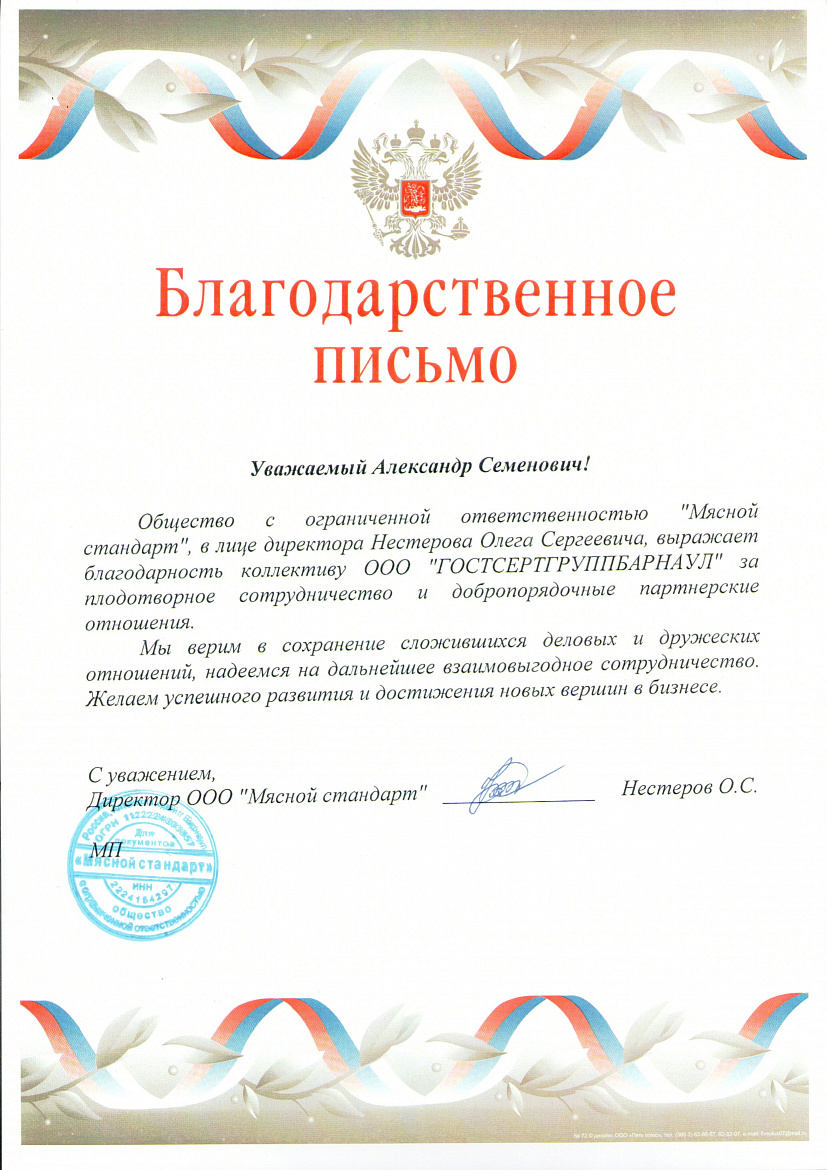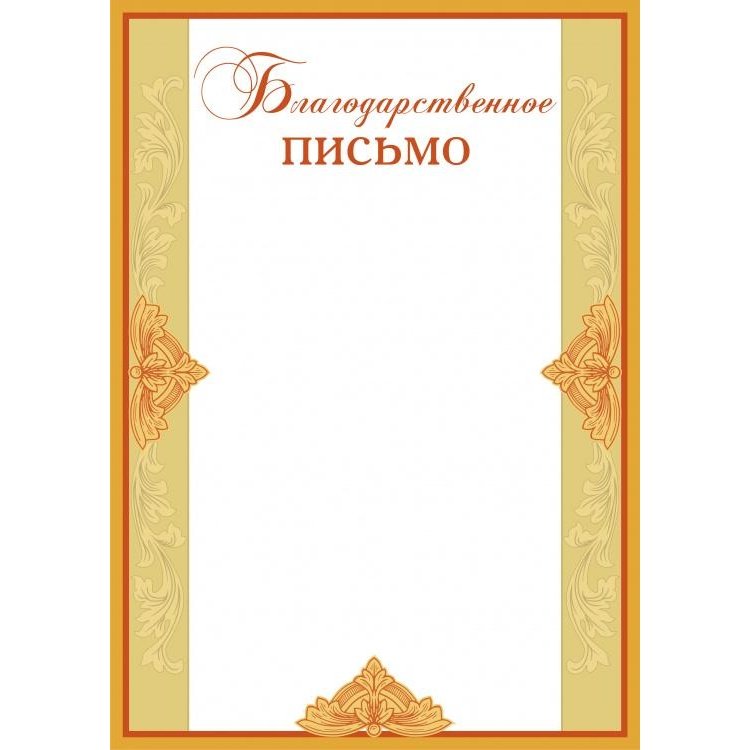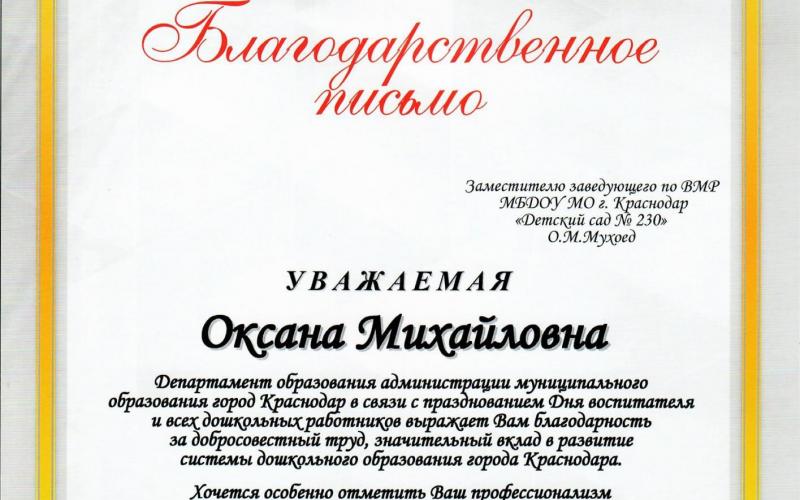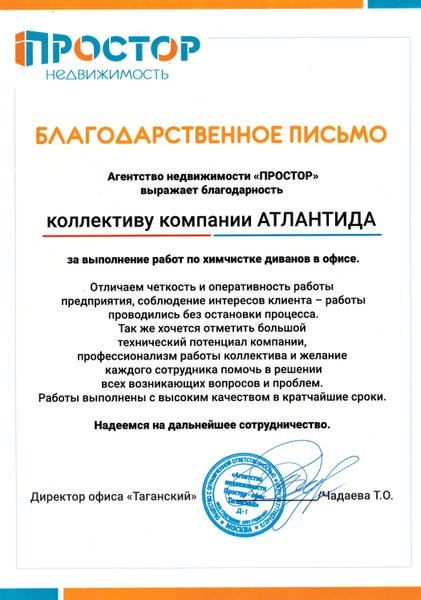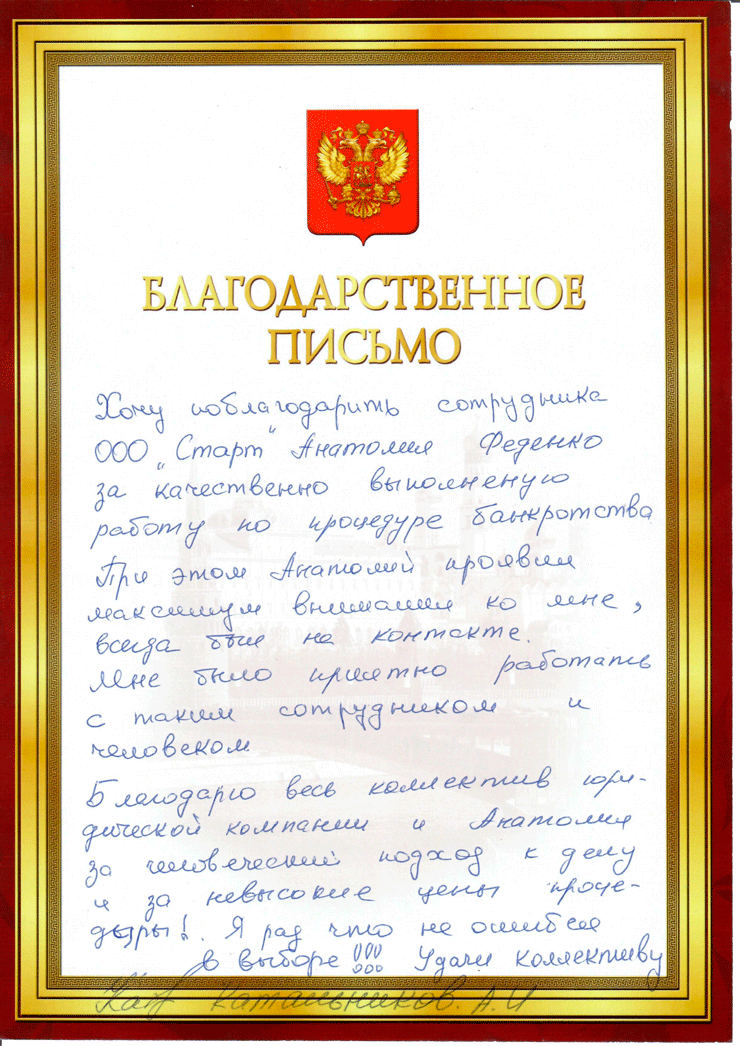
3 совета по правильному использованию шрифтов в электронных письмах / Хабр
Вы когда-нибудь задумывались о том, почему выбранный вами шрифт для электронного письма не отображался в почтовом ящике? Вероятно, это случалось, потому что ваш шрифт не был «безопасным», и устройство, на котором открывали письмо, его не поддерживало. В этой статье мы рассмотрим понятие «веб-безопасности» шрифтов, способы использования стандартных и нестандартных шрифтов, а также лучшие примеры их использования в email-рассылках.
Безусловно, одним из наиболее важных элементов проектирования является печатный текст. А графическое оформление и стиль текста называют типографикой. При правильном подходе типографика может преобразить ваши электронные письма. Однако проблема заключается в том, что не все шрифты отображаются во всех почтовых ящиках и на всех устройствах. Для начала нужно определиться с границами «веб-безопасности».
«Небезопасные» шрифты и как ими пользоваться
Определенные шрифты будут корректно отображаться абсолютно на всех устройствах и во всех почтовых клиентах.
Это так называемые «веб-безопасные» шрифты:
- Arial
- Courier
- Georgia
- Helvetica
- Lucida Sans
- Tahoma
- Times New Roman
- Trebuchet MS
- Verdana
А поскольку они отображаются везде, то вы можете смело использовать их в своих email-маркетинговых кампаниях. Единственным недостатком этих шрифтов является их весьма ограниченное количество.
В таком случае, что остается делать проектировщикам интерфейсов? К счастью, существует несколько способов решения этой проблемы.
Во-первых, при грамотной верстке писем нужно использовать не только шрифты, но и изображения, отступы, пробелы, работать с текстом и т. п. Об этом мы поговорим позже.
Во-вторых, выйти за границы «веб-безопасности» можно, набирая текст нестандартными шрифтами. Одним из популярных способов является использование веб-шрифтов, которые скачиваются при открытии сообщения, например, с сервиса Google web fonts.
А теперь давайте вернемся к проектированию электронных писем и типографике. Правильно подобрать шрифт для кампании email-маркетинга вам помогут 3 совета.
Совет №1: Выберите правильный шрифт для основного текста письма
В прошлом году на сайте компании Bloomberg была опубликована статья под названием «Шрифт ваших писем портит вам жизнь», автор которой пришел к выводу, что такие шрифты, как Arial и Helvetica не слишком подходят для чтения писем на ходу [мы уже переводили этот материал в нашем блоге – его можно прочитать
– прим. перев.]. Почему? Потому что формы некоторых букв – таких, как p, b, q, d – слишком схожи между собой, и читателю трудно их различить. «Вам следует использовать шрифт, в котором буквы не сливаются друг с другом», – дал совет профессор шрифтового дизайна Джерри Леонидас (Gerry Leonidas). Засечки, характерные для шрифтов семейства serif, придают каждой букве уникальность.
Напоминаем, как выглядят буквы с засечками и без них:
Какие шрифты рекомендуется использовать при верстке электронных писем в качестве альтернативы для Arial и Helvetica? Georgia или Verdana. «Что касается электронных писем, мы обычно просматриваем пару абзацев», – говорится в статье. – Широкое расстояние между буквами значительно ускоряет чтение… А серифы помогают различить буквы между собой».
В своем почтовом ящике мы нашли несколько хороших примеров использования шрифтов с засечками. Глобальная образовательная компания General Assembly, как правило, использует шрифт Georgia для основного текста письма:
Британская компания Dunhill, специализирующаяся на производстве мужских товаров класса люкс, также отдает предпочтение Georgia:
И кулинарный сайт The Kitchn делает выбор в пользу шрифта Georgia:
Но мы также обнаружили множество писем, в которых были использованы шрифты семейства sans serifs.
Чаще всего шрифты без засечек выбирают для небольших блоков текста (1 или 2 строки) или крупных заголовков, как в этом письме от сайта Canopy:
Американский бренд спортивной одежды премиум-класса Lululemon также отдает предпочтение шрифту без засечек:
Выводы
По общему правилу, если основной текст письма состоит из длинных блоков, следует использовать шрифты с засечками. Шрифты Georgia и Verdana делают текст более удобным для чтения. Однако для кратких писем и отдельных отрывков текста больше подходят шрифты без засечек.
Совет №2: Выделите заголовок с помощью комбинирования шрифтов или изменения стиля шрифта
Заголовки определяют структуру письма, разбивают текст на разделы, а содержание – на отдельные элементы. С их помощью читателю легче просмотреть и усвоить ваше сообщение. Выделить заголовок и сделать email более читабельным можно несколькими способами:
а) Для заголовка используйте тот же шрифт, что и для основного текста письма, но большего размера (и/или примените другой цвет и стиль, например, выделив его жирным или набрав только заглавными буквами).![]()
- Обращение.
- Содержание. Здесь должна быть отражена суть письма.
- Информация о составителе.
Рассмотрим эти пункты подробнее.
Обращение
На предприятиях традиционно принята формулировка «Уважаемая (-ый)…». Такое обращение свидетельствует об уважительном отношении к адресату.
При составлении письма не рекомендуется употреблять фразы «Дорогая (-ой)» или «Госпожа (господин)». Если, например, поощряется работник, то такое обращение будет выглядеть несколько несуразно и даже неискренне.